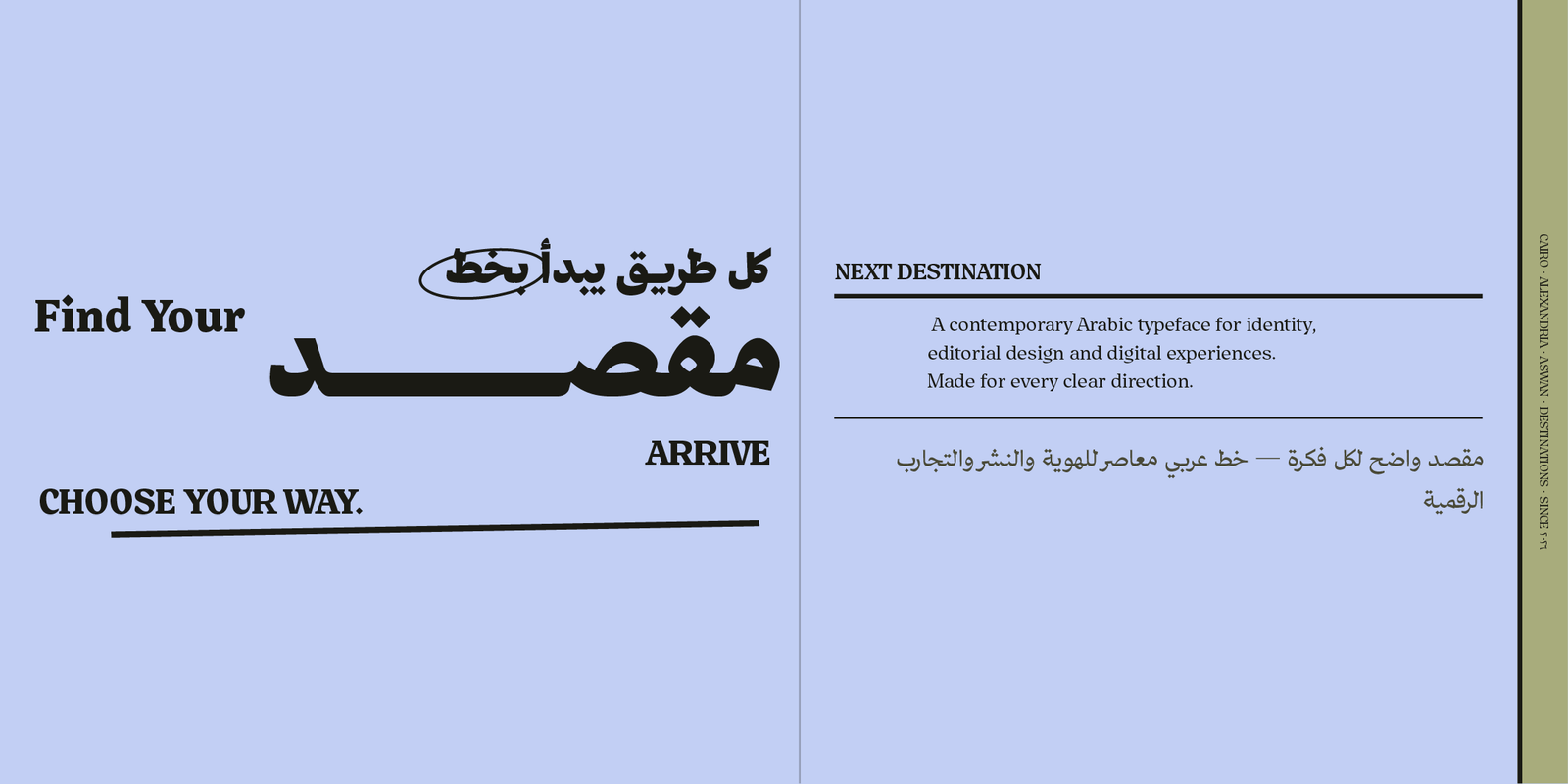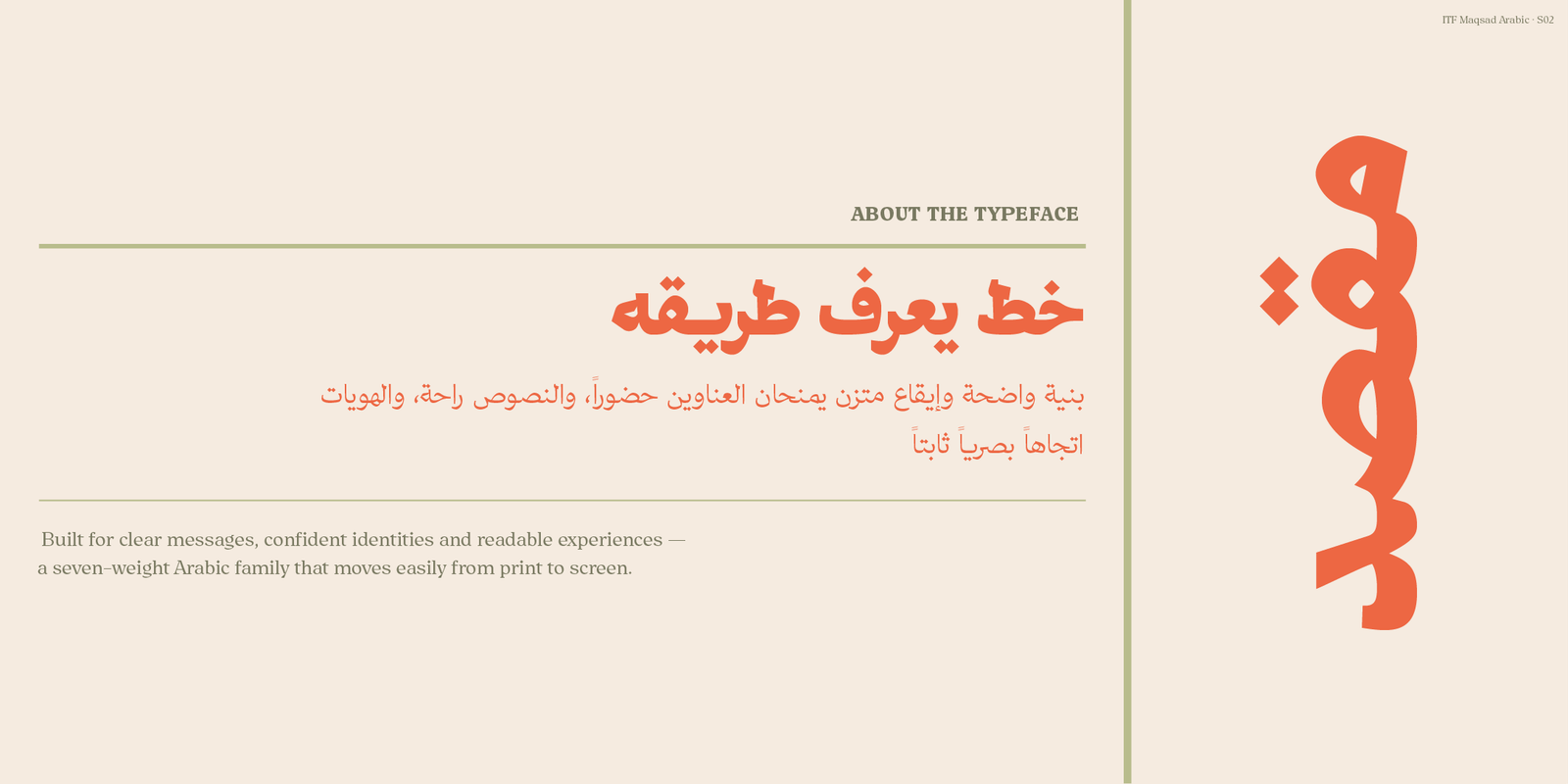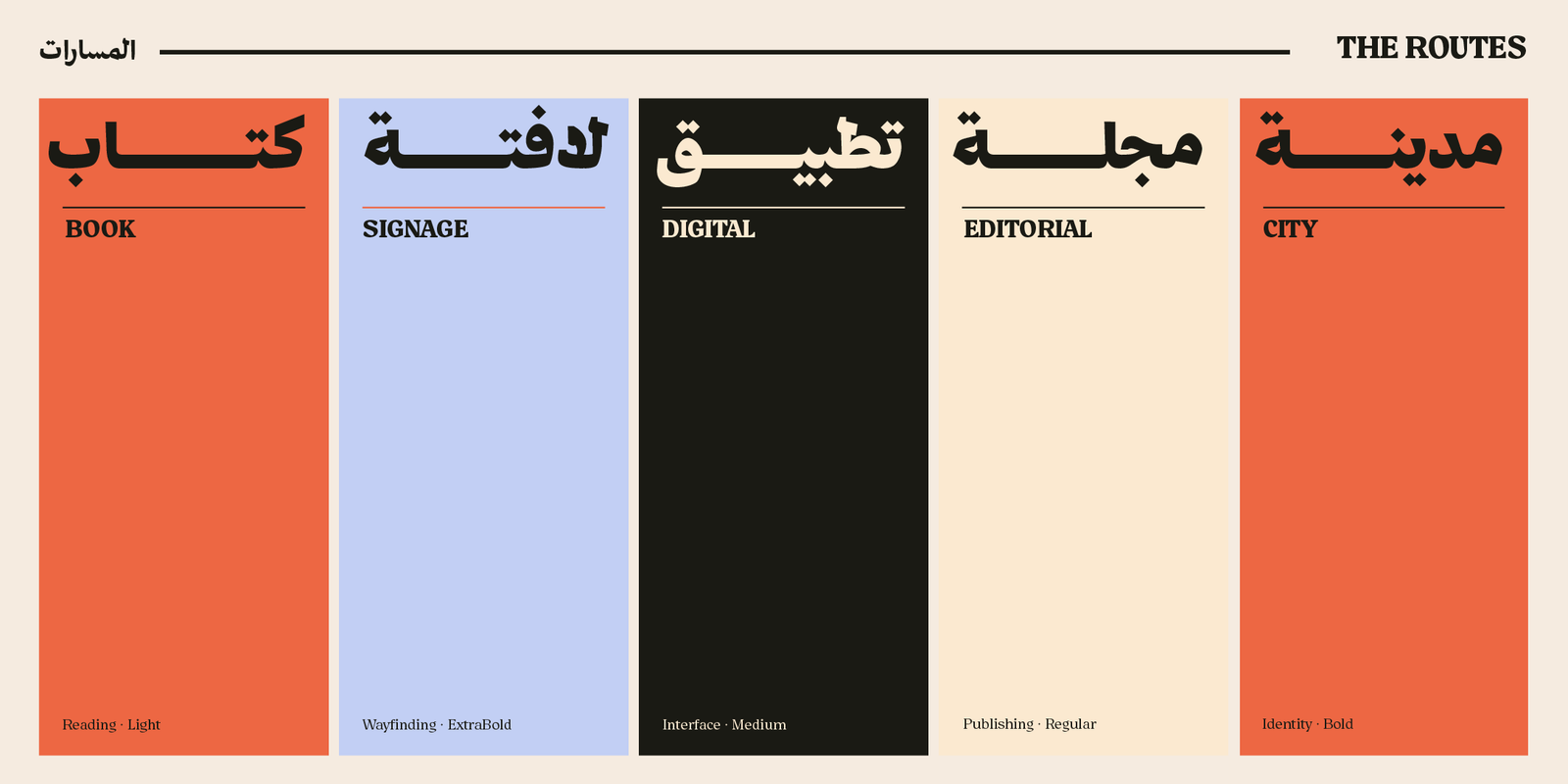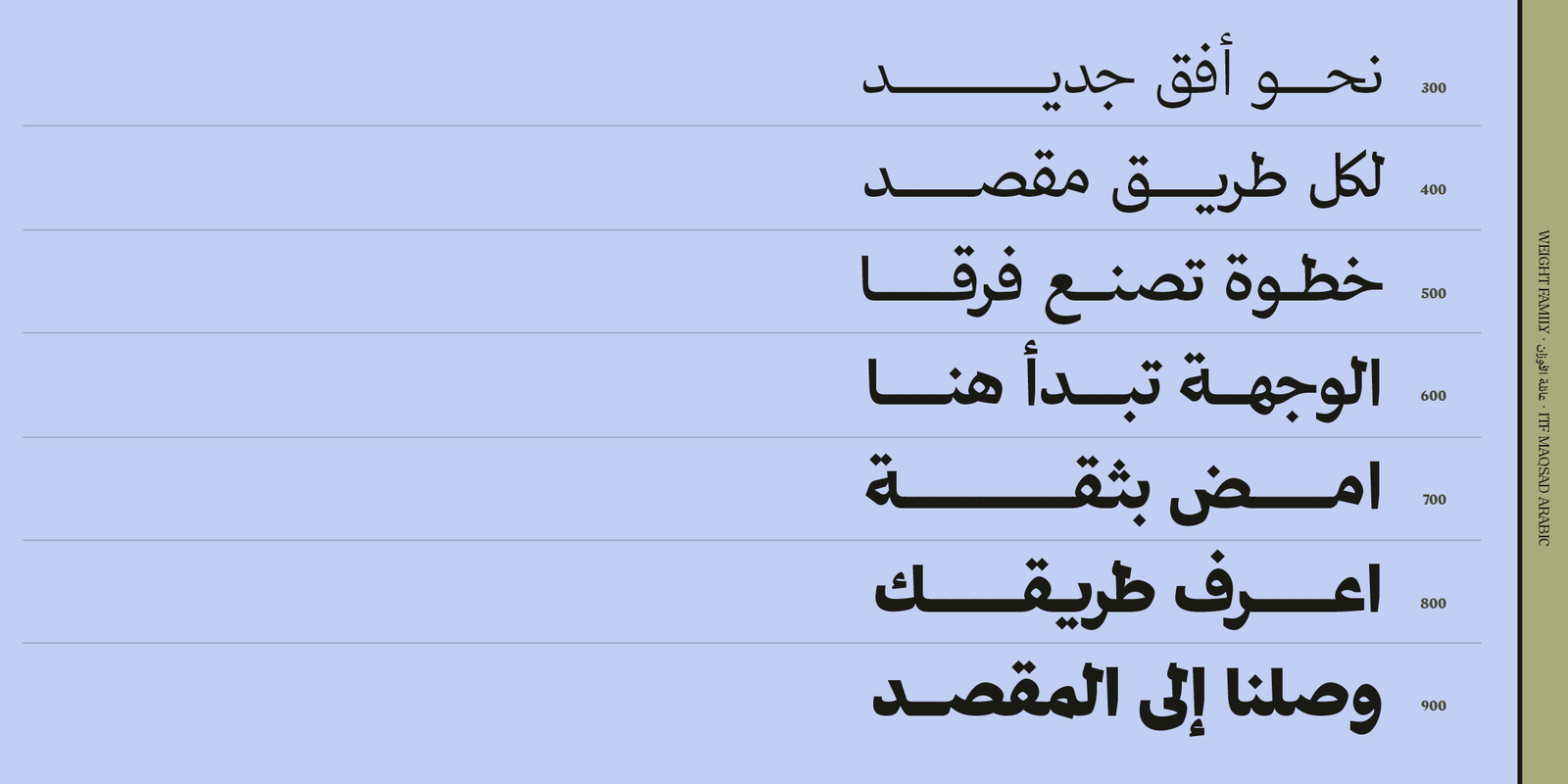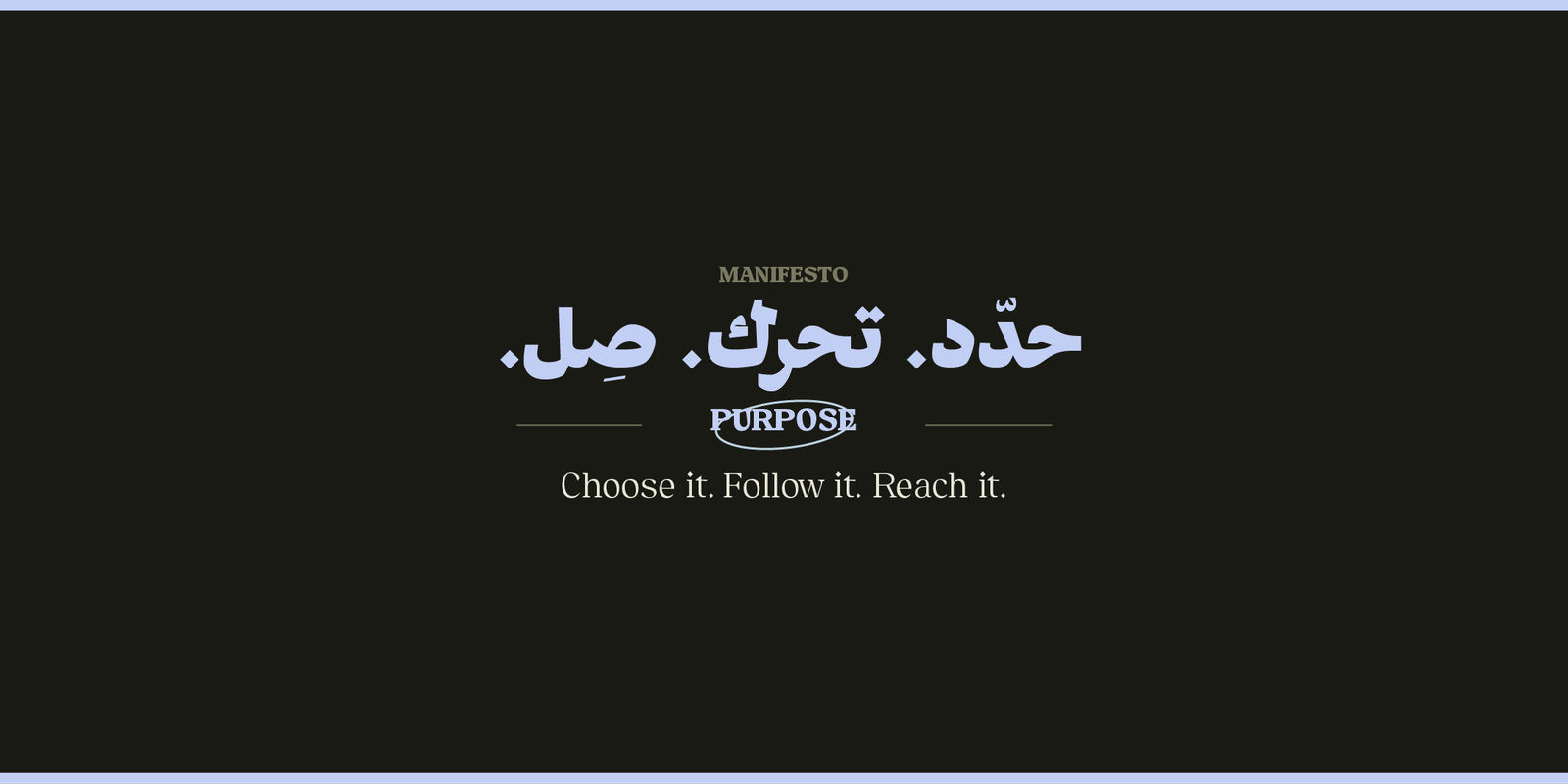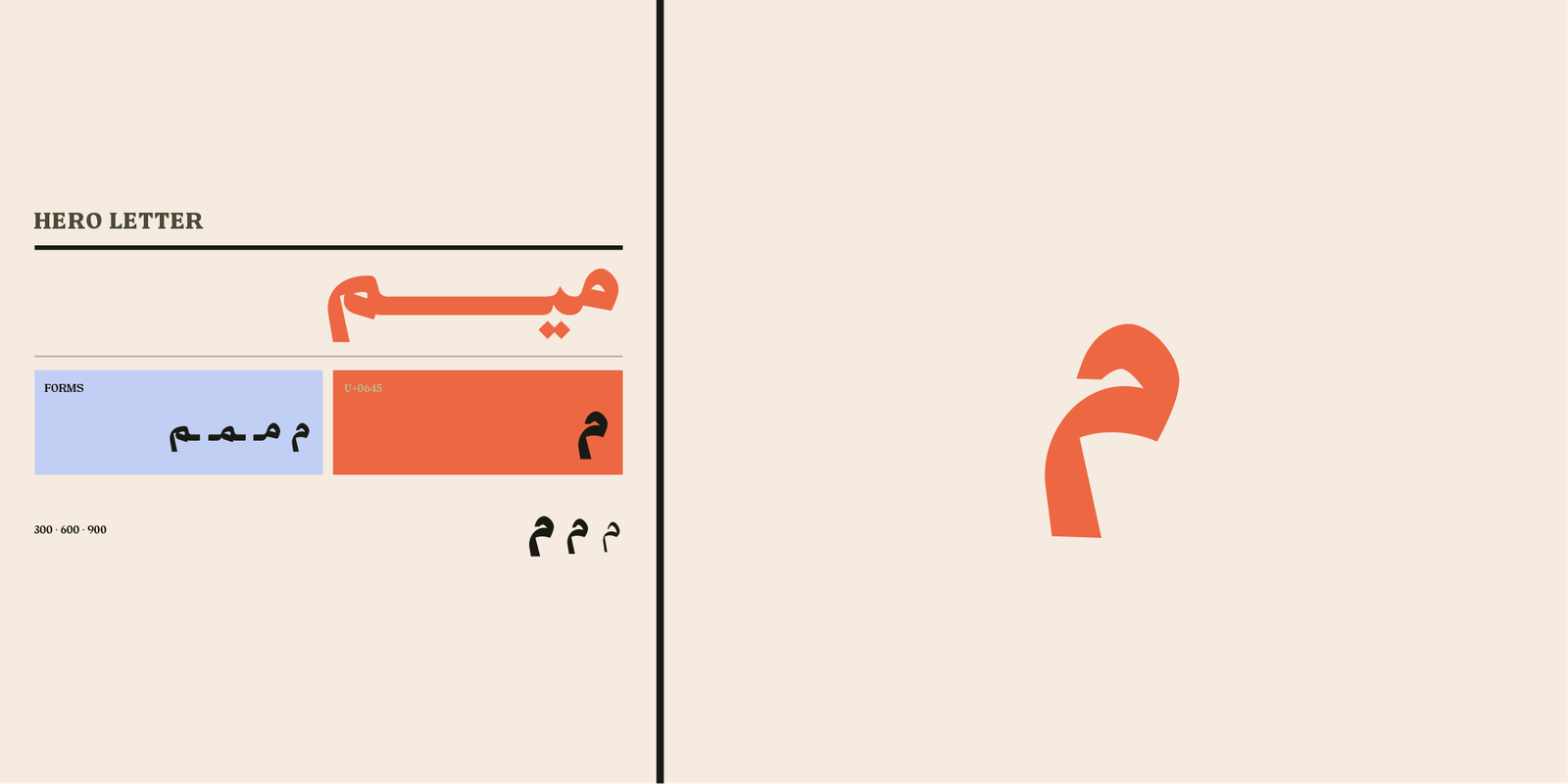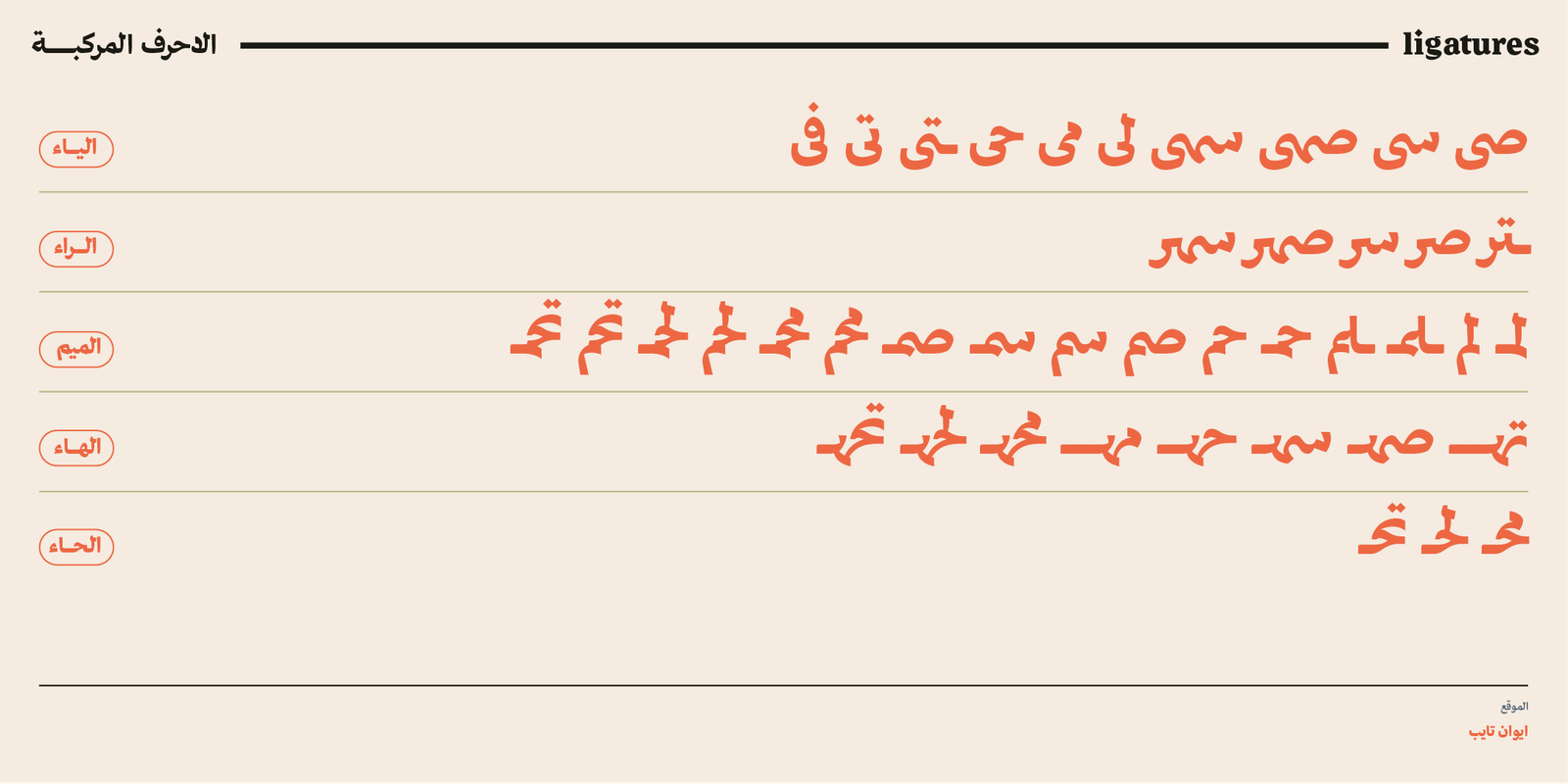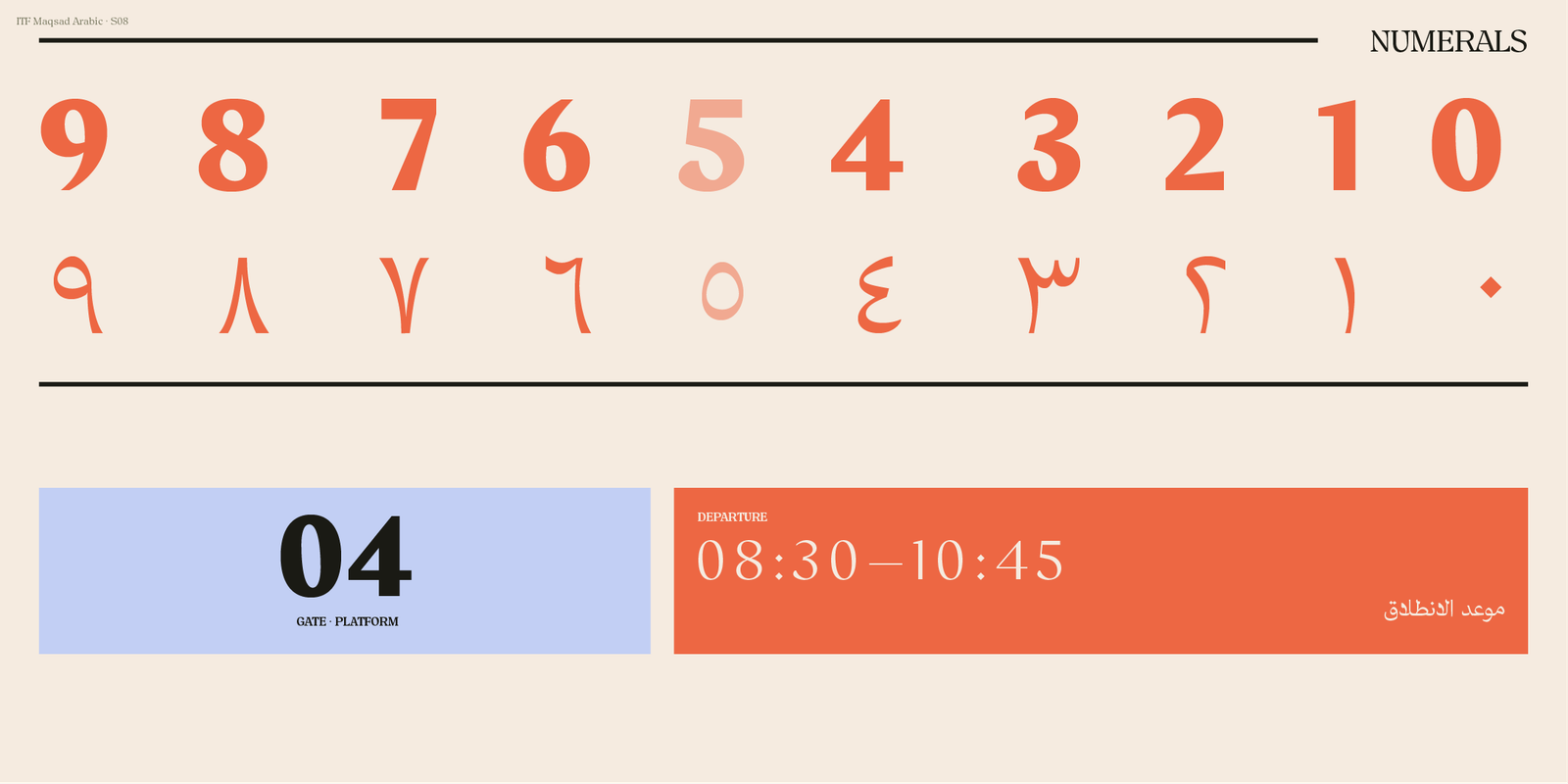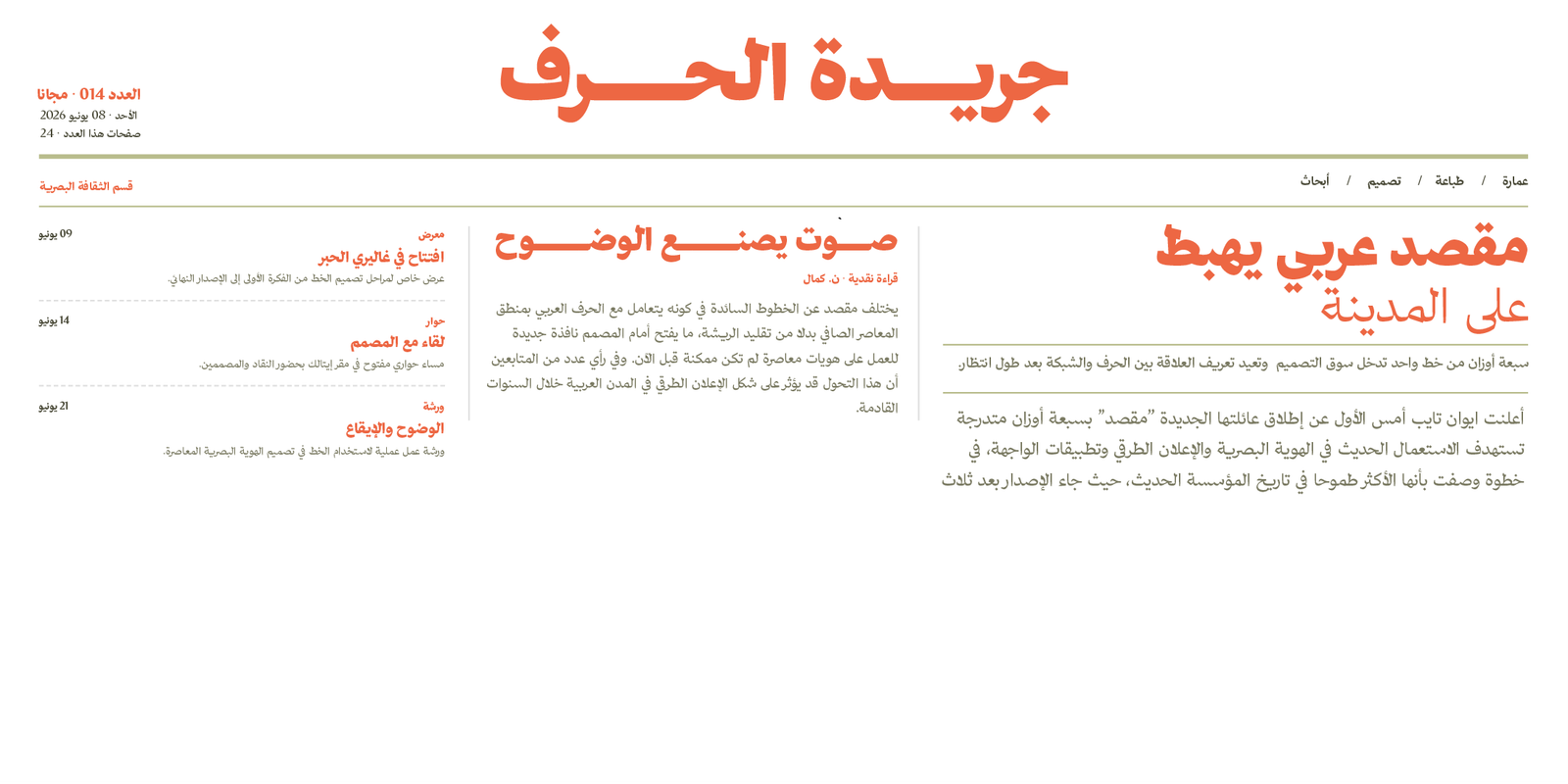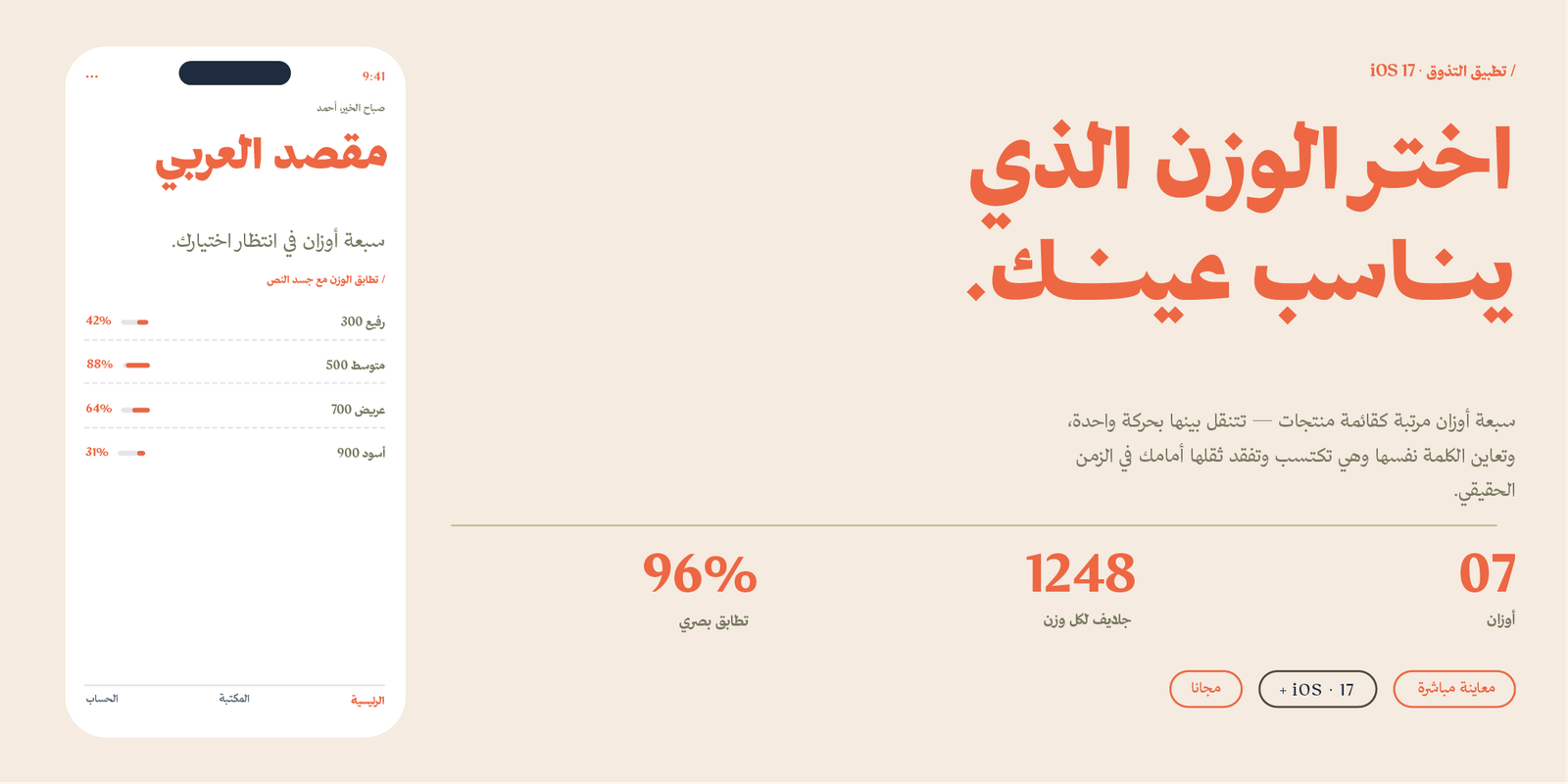
خط مقصد – Maqsad typeface – خط نسخ حديث
خط «مقصد» خط عربي حديث يجمع بين البنية الواضحة والتفاصيل الحادة، ليمنح الكلمات حضورًا قويًا دون أن يفقدها سهولة القراءة.
تتوازن في حروفه المساحات المفتوحة مع الامتدادات الأفقية والقطوع المميّزة، فتظهر شخصيته بوضوح في العناوين، وتبقى متماسكة في النصوص القصيرة والأحجام الأصغر.
تضم العائلة سبعة أوزان متدرجة من الخفيف إلى شديد السُمك، إلى جانب نسخة متغيرة تتيح تحكمًا مرنًا ودقيقًا في الوزن وطول الكشيدة، بما يمنح المصمم مساحة أوسع لضبط الإيقاع وبناء التكوينات الطباعية.
يناسب «مقصد» الهويات البصرية، والحملات الإعلانية، والتغليف، والمطبوعات والمنصات الرقمية، خاصةً حين يحتاج المشروع إلى خط واضح، واثق، وذي شخصية مميزة.
مميزات خط مقصد:
يتضمن الخط العديد من مزايا OpenType التي تضفي عليه مرونة وتنوعًا في الاستخدام، مثل:
- محورا استطالة في النسخة المتغيّرة يمدّان وصلات الكلمة تدريجيًا للعناوين الممتدة.
- أحرف مرسلة (تُفعَّل بإضافة “ءء” بعد الحرف) لضمان عملها على Canva، والأجهزة المحمولة، والتطبيقات التي لا تدعم ميزات OpenType.
- حرف ياء بنزول أقل: يقلل من نزول السطر ويعزّز انتظام النصوص.
- أحرف مركّبة تُحسّن سلاسة التراكيب وتناسق النص.
- سبعة أوزان كاملة تمنح مرونة واسعة في الاستخدام الطباعي.
- يدعم رمز الريال السعودي والريال العُماني ،ويتم تفعيلهما تلقائيًا عند كتابة الاختصارات: ر.س للريال السعودي ر.ع للريال العُماني